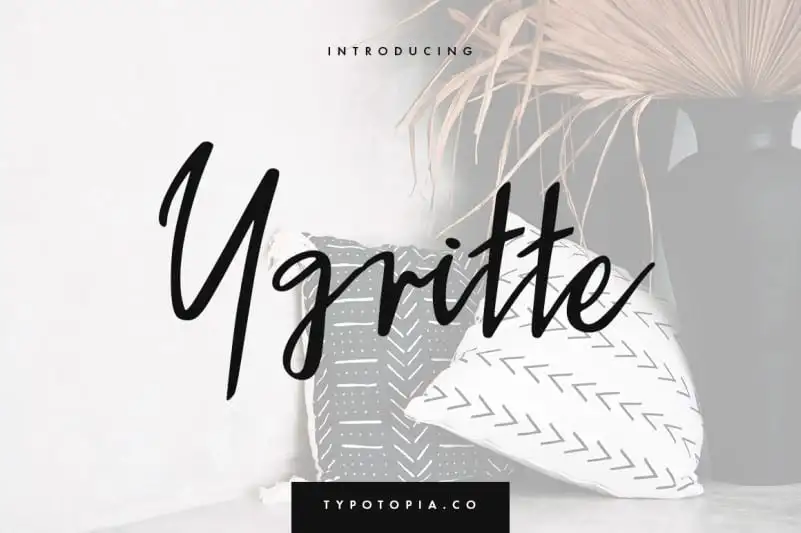
Ygritte Script Font – Download Grátis
A Ygritte Script Font é uma elegante tipografia feita à mão, com um ar descontraído que transmite uma sensação amigável e alegre. Perfeita para uso em sites, impressão ou vídeos animados, o Spicy Burger manterá seu design único e impecável. Seja você desenvolvedor de jogos, designer gráfico ou editor de imagens, Ygritte Script Font é perfeito para aqueles que valorizam um toque criativo sem comprometer a qualidade. Para quem desejar usar essa fonte em um ambiente comercial, por favor, compre uma licença comercial aqui. O uso personalizado está liberado, mas não autorizado comercialmente. A Ygritte Script Font é uma excelente adição para aqueles que procuram uma tipografia versátil e bonita para seus projetos digitais ou impressos.